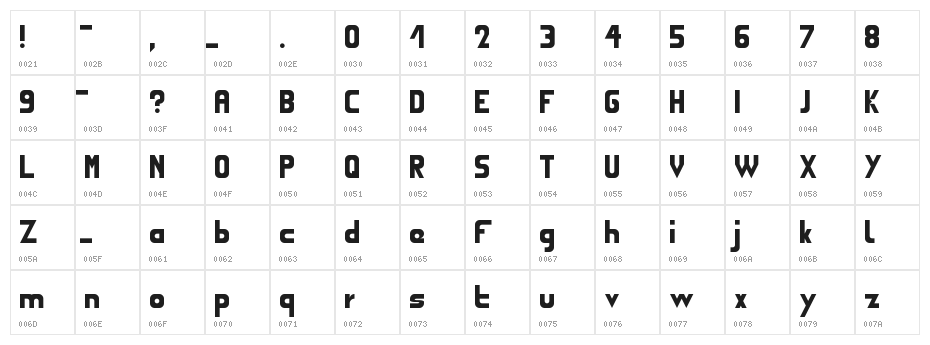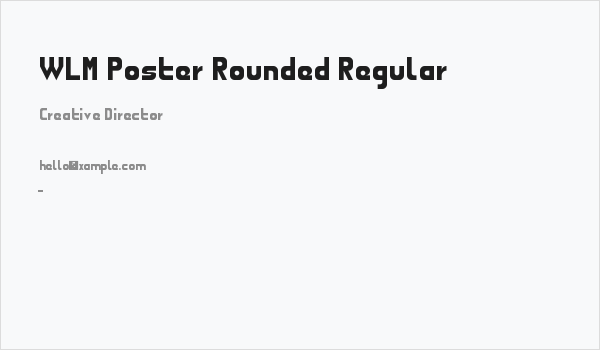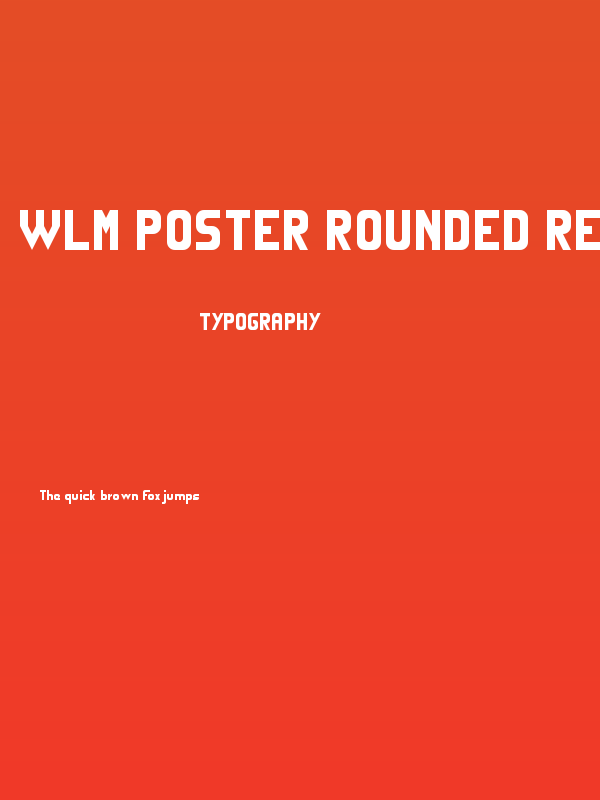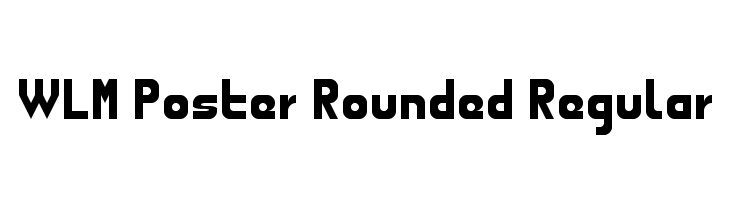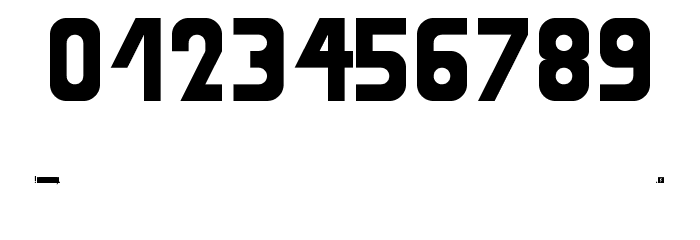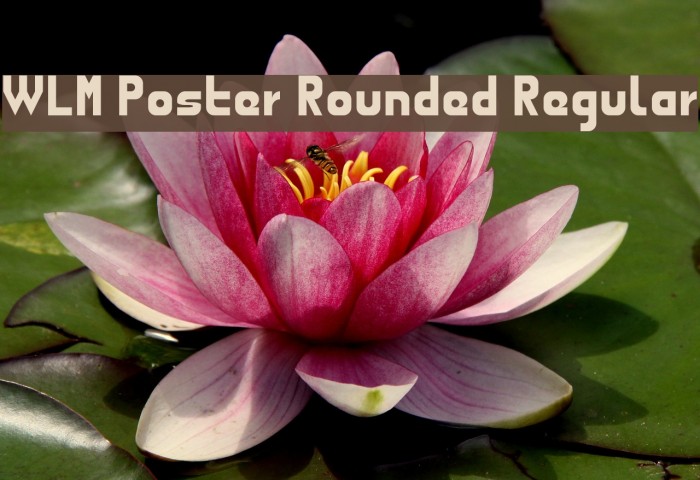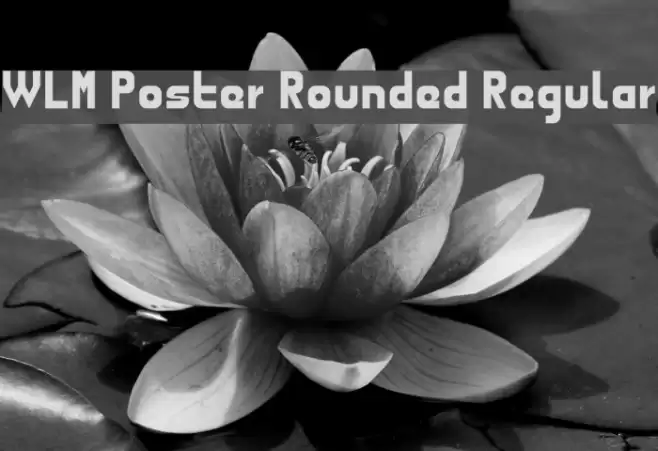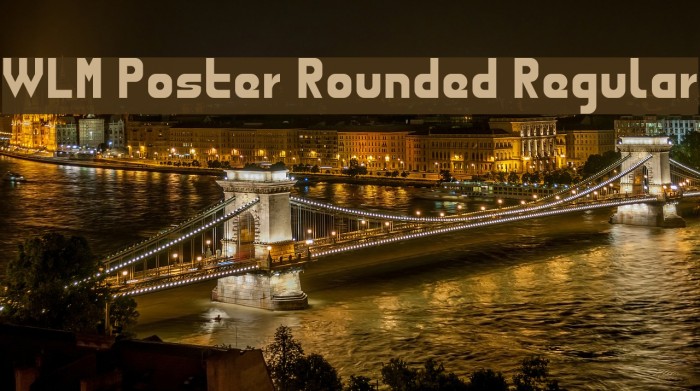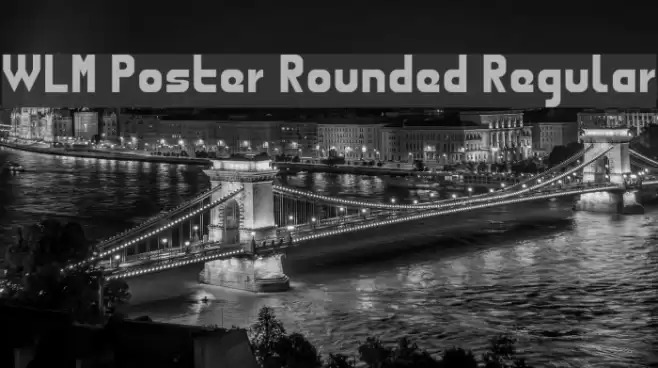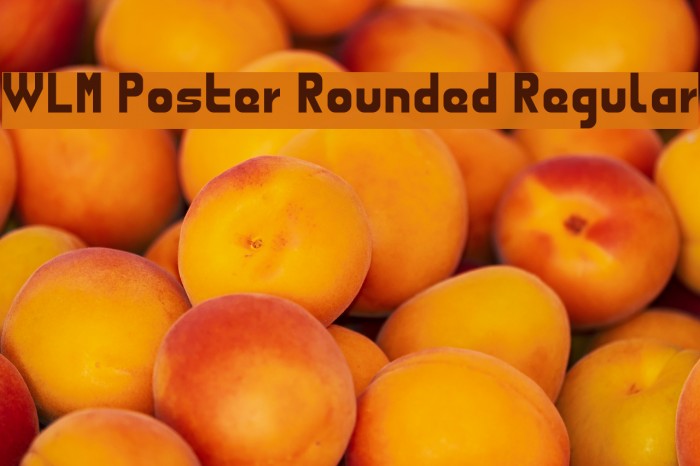
WLM Poster Rounded Regular Font
| Vorgeschlagene Projekte | Ideal for posters, headlines, branding, and advertising materials that require a bold and modern look. |